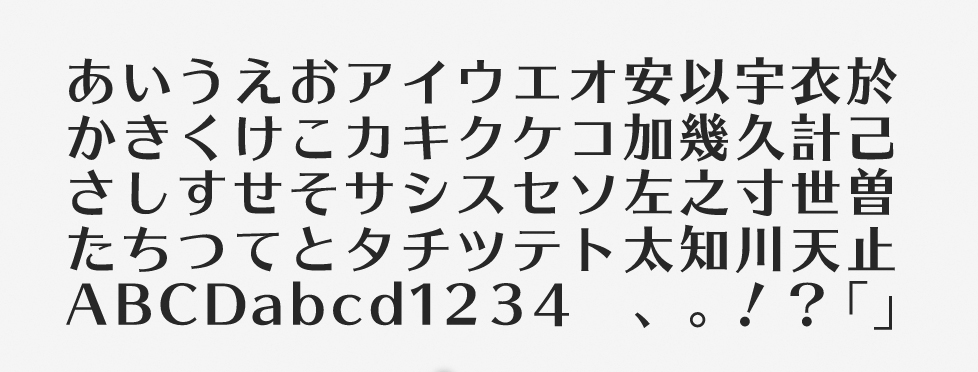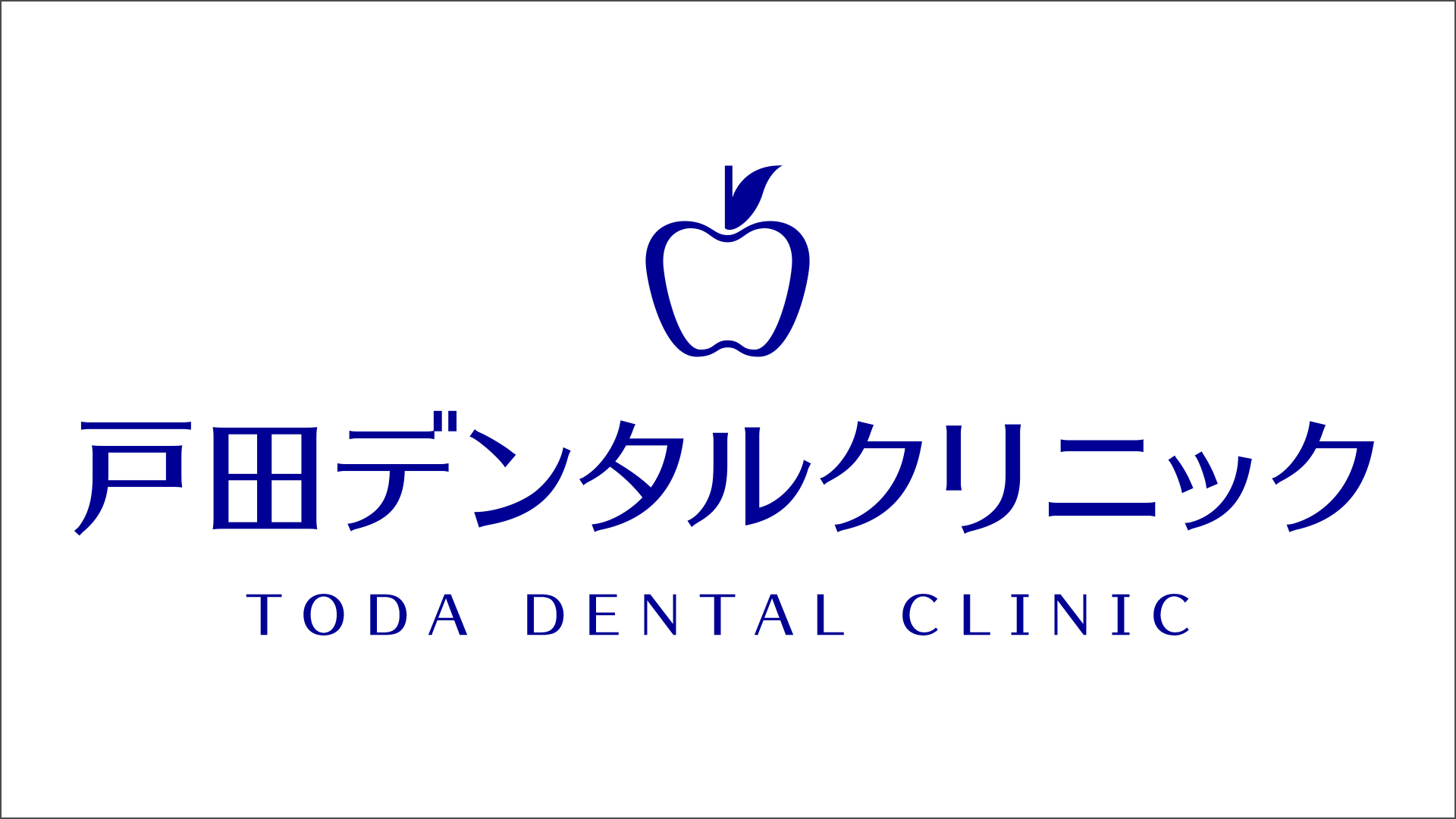
「UDタイポス」について
タイポス系の書体は、写植が用いられていた1960年代に、明朝体でもゴシック体でもない新たなデザイン書体として誕生しました。その発端となったのは、武蔵野美術学校の学生たちの卒業制作。新書体を研究・開発する「グループタイポ」という集団でした。UDタイポスは、タイプバンクのタイポスをユニバーサルデザイン化したフォントです。
「UDタイポス」の特徴
縦画と横画の太さに明確な差があり、きちんとした印象を与えつつもおしゃれに見えるフォントです。この線の太さの差は、ウエイトによっても異なります。縦横の差が小さいとゴシック体のようにも見えますが、差が大きいと独特な表情が特に強調されます。
明朝体やゴシック体と比べると、個性的な印象が強いフォントです。クリーンな雰囲気の制作物にもマッチしやすく、工夫のあるデザインでありながら、しっかりと可読性も高められています。
UDタイポスは、明朝体とゴシック体の中間に相当するスタイリッシュなフォントです。アルファベットも大変美しく、丁寧に組むとロゴタイプとしても使用できます。作例では「田」と下の「T」をセンター合わせにする工夫を施しました。主にタイトルや見出しとしての使用をおすすめしたいフォントです。